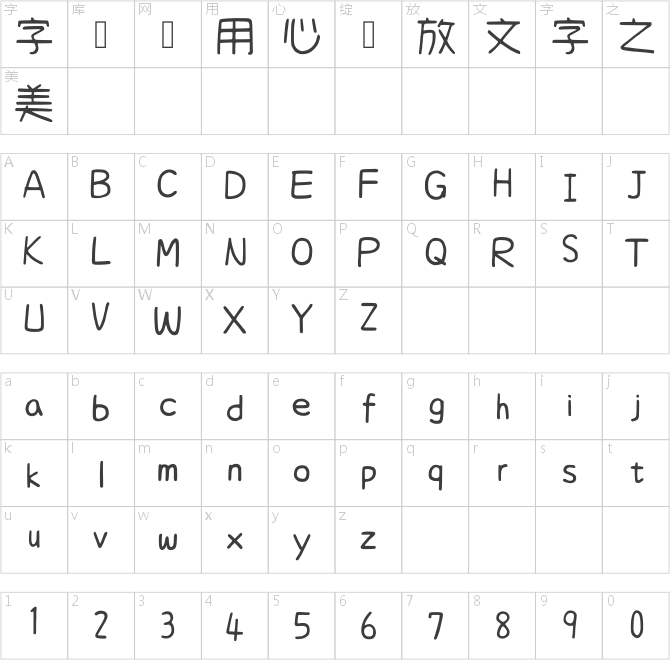
字體名稱: 清松手寫體4
清松手寫體4
清松手寫體系列是游清松在稿紙上用原子筆手寫,透過「守寫字」網站產生出初稿字型檔,再透過字型軟件后制加工而成的手寫字型。目前已經發布4套不同風格的清松手寫體。手寫清松體1清松手寫體2清松手寫體3、清松手寫體4
清松手寫體4字體清松手寫體4字庫是一款讓人賞心悅目、百看不厭的中文字體,適合各類廣告和產品包裝設計應用,字體大小3.94MB,格式為ttf字體,上傳用戶是KISEKI,作者/版權方為游清松